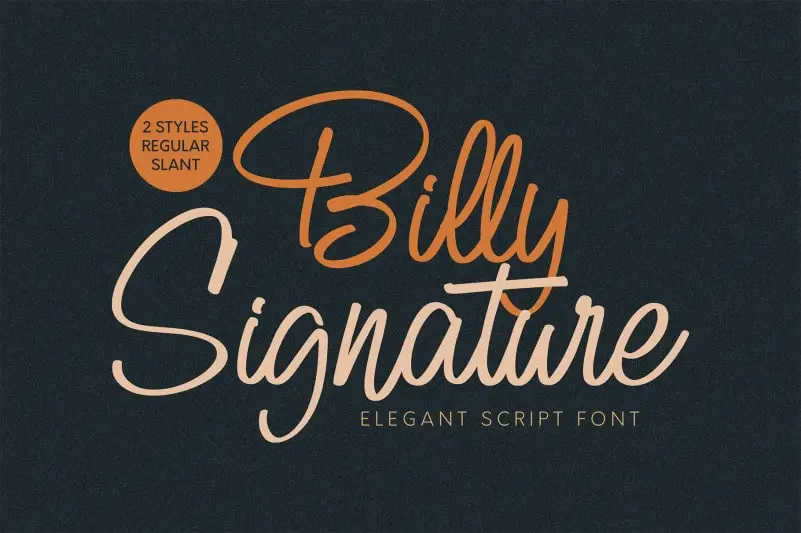
A fonte “Billy Script Font” é uma opção vibrante para aqueles que buscam estilos únicos no mundo dos desenhos digitais. Ela é uma criação cuidadosamente feita por sartstudio, disponível apenas no site da 99designs, e tem um formato de script elegante e único. A fonte “Billy Script Font” oferece dois estilos distintos: regular e inclinado. O seu charme reside na sua aparência natural e autêntica, que se deve à sua natureza artesanal, com traços finos, espessos, e um toque de sujeira, garantindo sempre uma beleza única em qualquer projeto de design. Com sua textura delicada e seus traços bem definidos, a “Billy Script Font” não apenas adiciona um toque distintivo às suas criações, mas também as torna mais autênticas e imersivas. Esta fonte é perfeita para aqueles que buscam uma fonte de script que combine elegância com naturalidade, proporcionando uma experiência visual enriquecida em qualquer projeto gráfico ou design de layout.